13 Mejores tipografías para web que aún no conocías
Es muy útil conocer fuentes gratuitas que puedes aplicar en tus diseños. A la hora de realizar proyectos editoriales y de diseño gráfico, la elección de la tipografía es fundamental, ya que en gran medida, de una correcta elección dependerá que impacte más o menos. Pues bien, en lo referente a las páginas web, ocurre lo mismo.
Y no es nada sencillo escoger la que mejor pueda funcionar para nuestro proyecto.
¿Cómo escoger las mejores tipografías para web?
La tarea de encontrar las mejores tipografías para web puede resultar realmente abrumadora. Tras una búsqueda, podemos decir que hay más de 1.000 familias de fuentes de Google, casi 2.000 fuentes de Adobe, 15.000 fuentes en Fonts.com y casi 35.000 fuentes en MyFonts.com.
¿Entonces, cómo podemos hacer una buena elección?
Para realizar la selección de fuentes para este artículo, nos hemos basado en algunos criterios como son los siguientes:
- Legibilidad: una de las características principales de una tipografía es que cada uno de los caracteres se distingan correctamente. Eso ayudará a mejorar la accesibilidad y la lectura de la web.
- Que sean aptas para el lugar donde se van a usar: fuentes diseñadas para su uso en partes específicas del sitio (es decir, fuentes grandes y en negrita en los encabezados frente a fuentes limpias y de estilo simple en el cuerpo).
- Fuentes con la que sea fácil familiarizarse: es necesario que los usuarios se sientan cómodos al leerlas. Todo aquello que se aleje demasiado de la norma puede crear una experiencia desconcertante para los visitantes y los tipos de letra inesperados o poco comunes pueden ayudar considerablemente.
Otra cuestión a considerar es el peso de la misma. Una tipografía que pese mucho puede ralentizar la carga de la web, afectando al posicionamiento web.
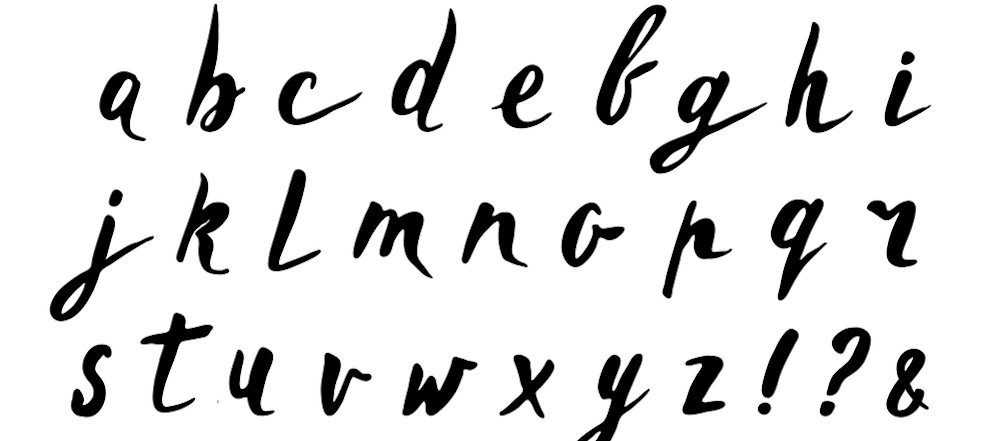
Estas son algunas tipografías perfectas que no conocías
Como ya sabes, existe una gran cantidad de fuentes, pero en caso de que no hayas sido capaz de escoger una entre las mejores tipografías para web, la selección que hacemos para ti puede ser tremendamente útil.
Lato
La fuente Lato es una fuente de Google que se diseñó en un principio para un cliente. Posteriormente, esta tipografía se reutilizó y hoy en día es una de las que más se utilizan para páginas web. De hecho, se utiliza en sitios web como Goodreads, WebMD y Merriam-Webster. Gracias al equilibrio que existe en ella entre curvas suaves y diseño robusto, esta tipografía emite un mensaje potente pero suave al mismo tiempo.
Fuente Montserrat
Esta tipografía se inspira en una señalización presente en el barrio de Montserrat en Buenos Aires a inicios del s. XX. Se trata de una fuente perteneciente a la familia Sans Seriff, muy bonita, cuya misión es facilitar una lectura rápida del lugar donde se coloque. Por esa razón, es perfecta para usar en cuerpos de texto pequeños.
La tipografía Neue Helvética
La Neue Helvetica es la segunda fuente más popular en la web, con más de 218.000 sitios web como Facebook, Yahoo y eBay que la utilizan. Es una de las mejores tipografías para web porque es sencilla, fácil de leer y funciona perfectamente para encabezados o cuerpos.
Roboto
Conforme nuestra sociedad va avanzando tecnológicamente, la fuente Roboto se va haciendo más y más popular. El aspecto de esta tipografía es similar a una máquina, con caracteres abiertos.
En principio, Google la diseñó para que fuese parte de Android, pero hoy en día se usa en webs como YouTube, por ejemplo.
Las mejores tipografías para web Serif
Las fuentes serif tienen una estructura estable y predecible, lo que las hace perfectas para cuerpos o encabezados.
Lora
Esta tipografía es una serif contemporánea. Además de ser genial para la legibilidad de los textos, las pinceladas únicas al final de cada carácter proporcionan un aspecto más artístico que otras. Fox News usa esta fuente.
Merriweather
La Merriweather es una fuente que Google creó concretamente para mejorar la legibilidad en las pantallas. También tiene una versión sans serif, por lo que si tienes un blog u otra web con mucho texto, la combinación de estas dos fuentes funciona bien para mantener al usuario enfocado en el texto.
Spectral
Una de las fuentes de más reciente incorporación es la Spectral. Cuenta con 14 estilos diferentes.
Mejores tipografías para web: títulos y encabezados
En esta sección veremos algunas tipografías perfectas para usar en estos lugares estratégicos.
Abril Fatface
Se trata fuente de Google que se basa en titulares publicitarios de Gran Bretaña y Francia en el siglo XIX. El peso de la fuente aporta fuerza a cualquier título o encabezado al que se aplique. Por otro lado, las curvas de las letras y los números también transmiten una sensación de elegancia. Es perfecta para dar un toque de estilo clásico y europeo.
League Gothic
League Gothic funciona bien para la web, sobre todo cuando se usa para titulares y encabezados de empresas más serias. Una empresa que lo usa es Fox Sports.
Nexa y Raleway
La fuente Nexa no es solo una tipo limpia y elegante para usar en títulos o encabezados en páginas web, también funciona muy bien en diseño gráfico. Hay 18 estilos de fuentes en total en la familia, por lo que puedes usarla y hacer que siempre tenga un aspecto totalmente distinto.
Por otro lado, la fuente Raleway se diseñó para ser una fuente única, delgada y muy ligera. Sin embargo, durante la última década, esta familia de fuentes se ha ampliado con distintos grosores. También cuenta con un estilo alternativo que convierte esta fuente en una sans serif geométrica. Esta variedad de estilos da a los diseñadores web cierta flexibilidad en términos de dónde y cuándo deciden usarlo.
Mejores tipografías para web cursivas
Pero también podemos encontrar tipos cursivas. Veamos un par de ellas.
Milkshake
A diferencia de algunas fuentes cursivas que se parecen a la escritura a mano real, esta se adapta mejor a la ubicación en el texto del título y los logotipos. Esto no funciona bien para marcas más formales o tradicionales.
Mission script
Fuente cálida y con pinceladas divertidas y, sin embargo, un estilo muy realista. Funciona bien para webs de consultoría, entrenadores o autónomos que con audiencia femenina.
Como verás, hay muchas fuentes que puedes escoger para tu proyecto digital. Recuerda tener presente qué quieres transmitir para encajarlo con la mejor tipografía.